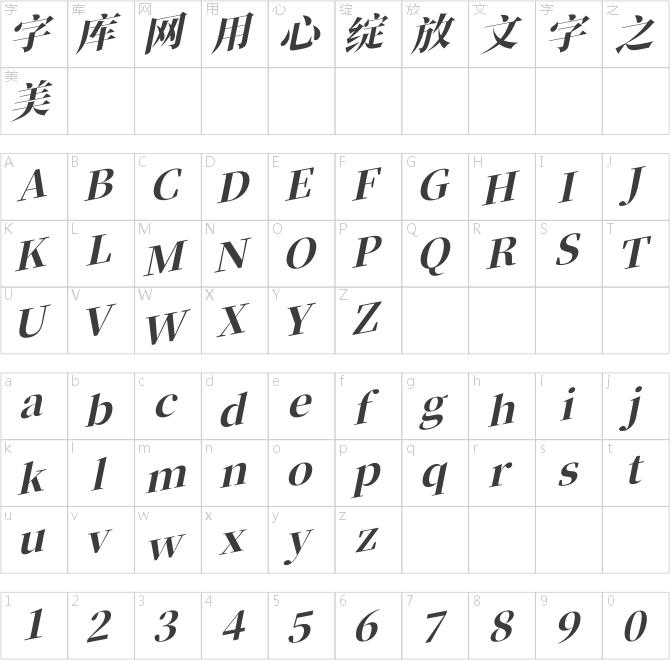
字体名称: 新愚公拼搏体
新愚公拼搏体
新愚公拼搏体介绍
基于“思源SC宋体”改造的一款免费商用字体。这款字体将横向与纵向的笔划一起切割,寻求达到线条与层次分明的机械装甲感,再向上和向右大幅度倾斜,力求营造一种奋勇前进、奋斗不息的张力,适用于广告。
新愚公拼搏体字体字库是一款让人赏心悦目、百看不厌的中文字体,适合各类广告和产品包装设计应用,字体大小15.61MB,格式为ttf字体,上传用户是KISEKI,作者/版权方为新愚公